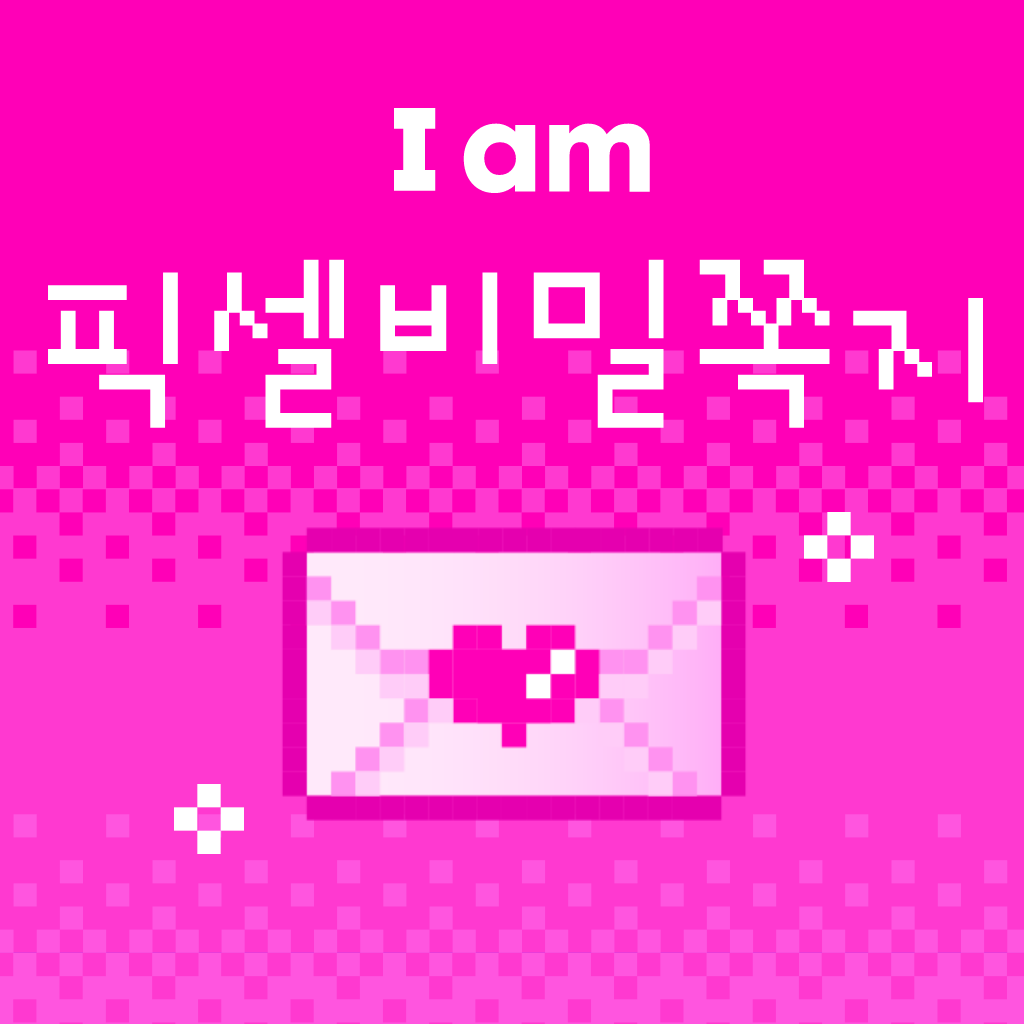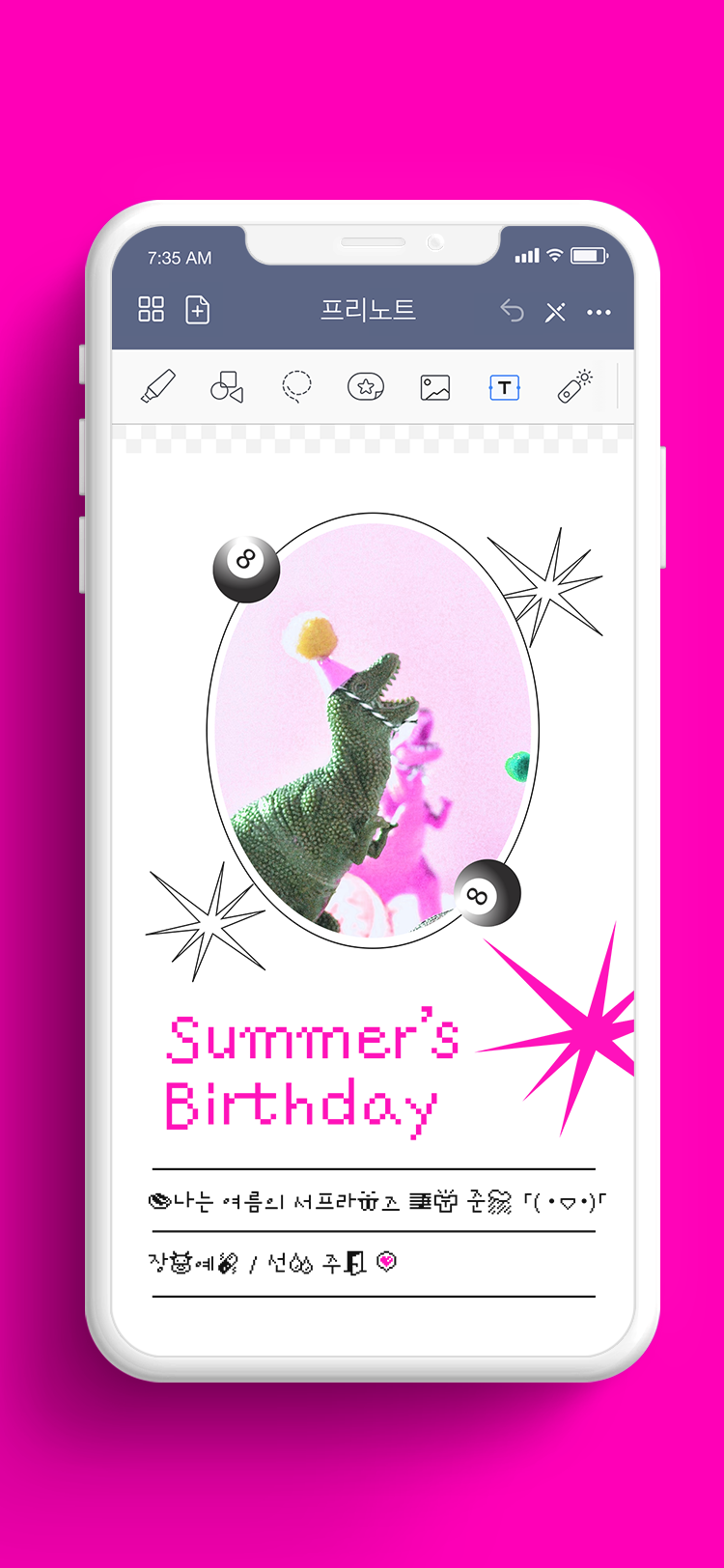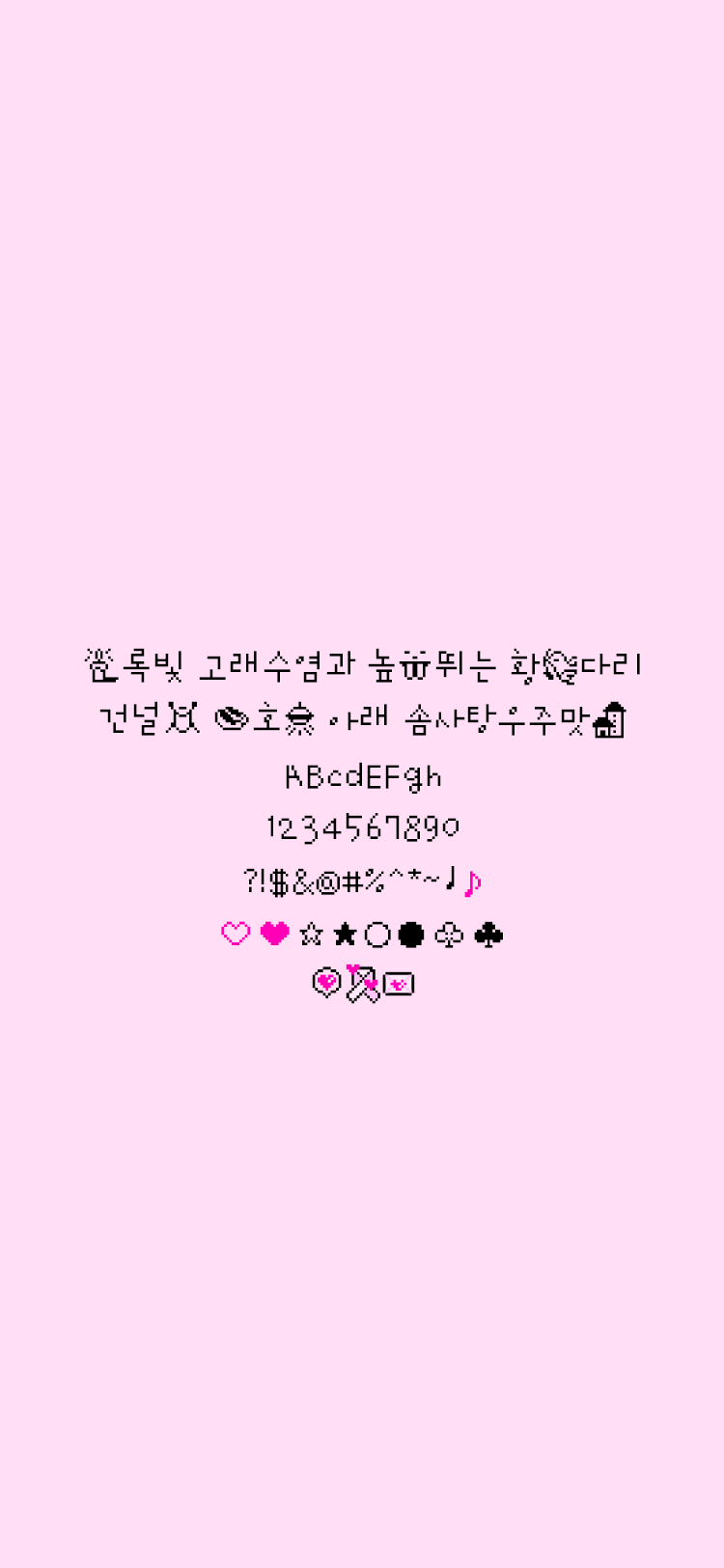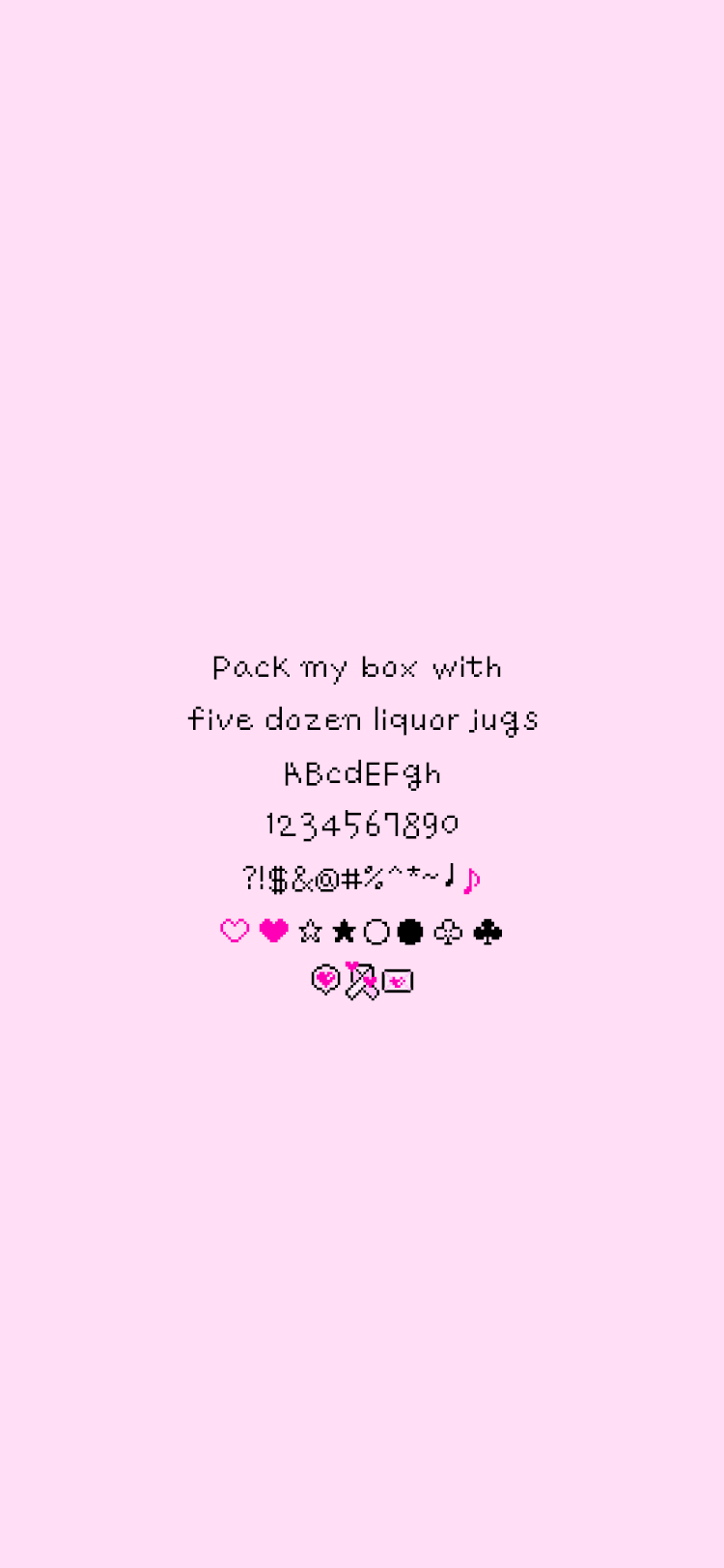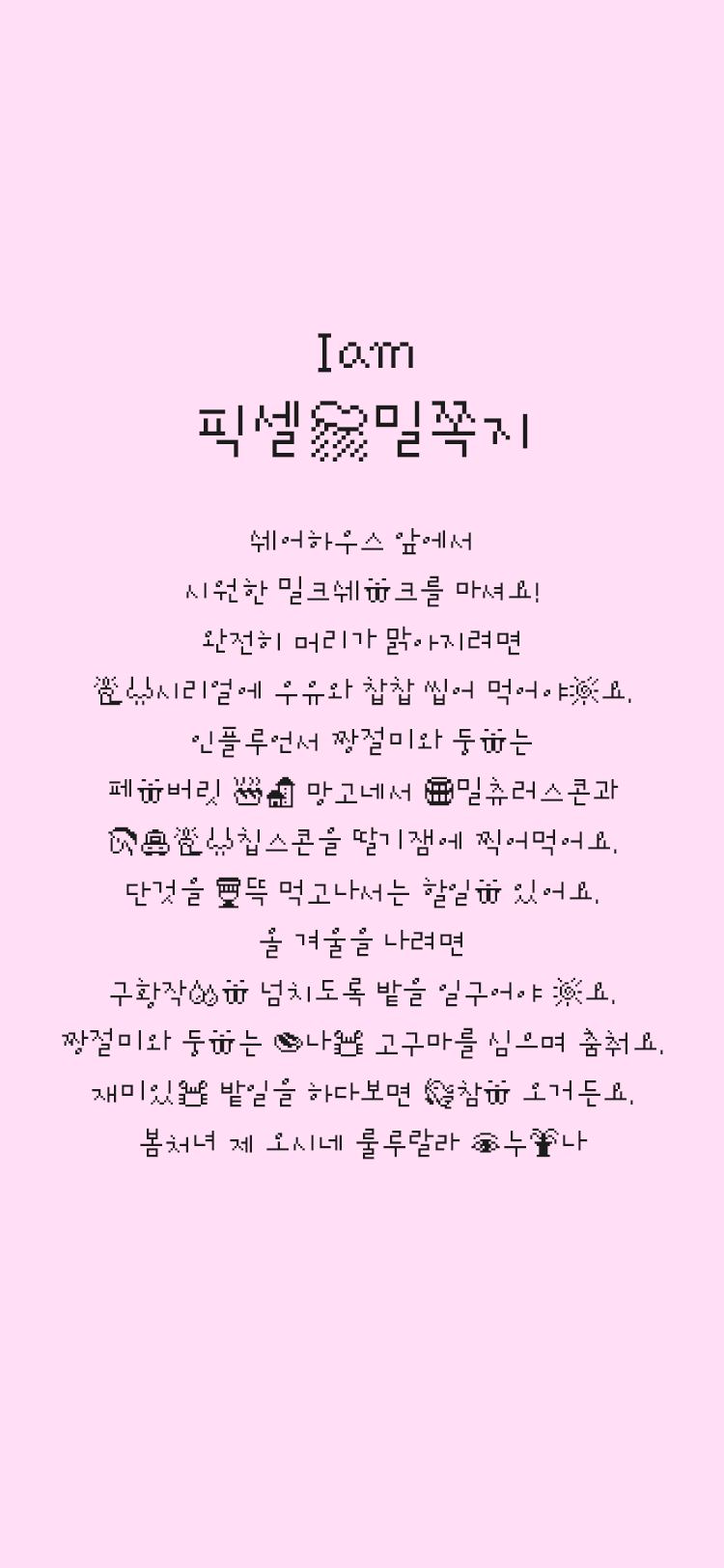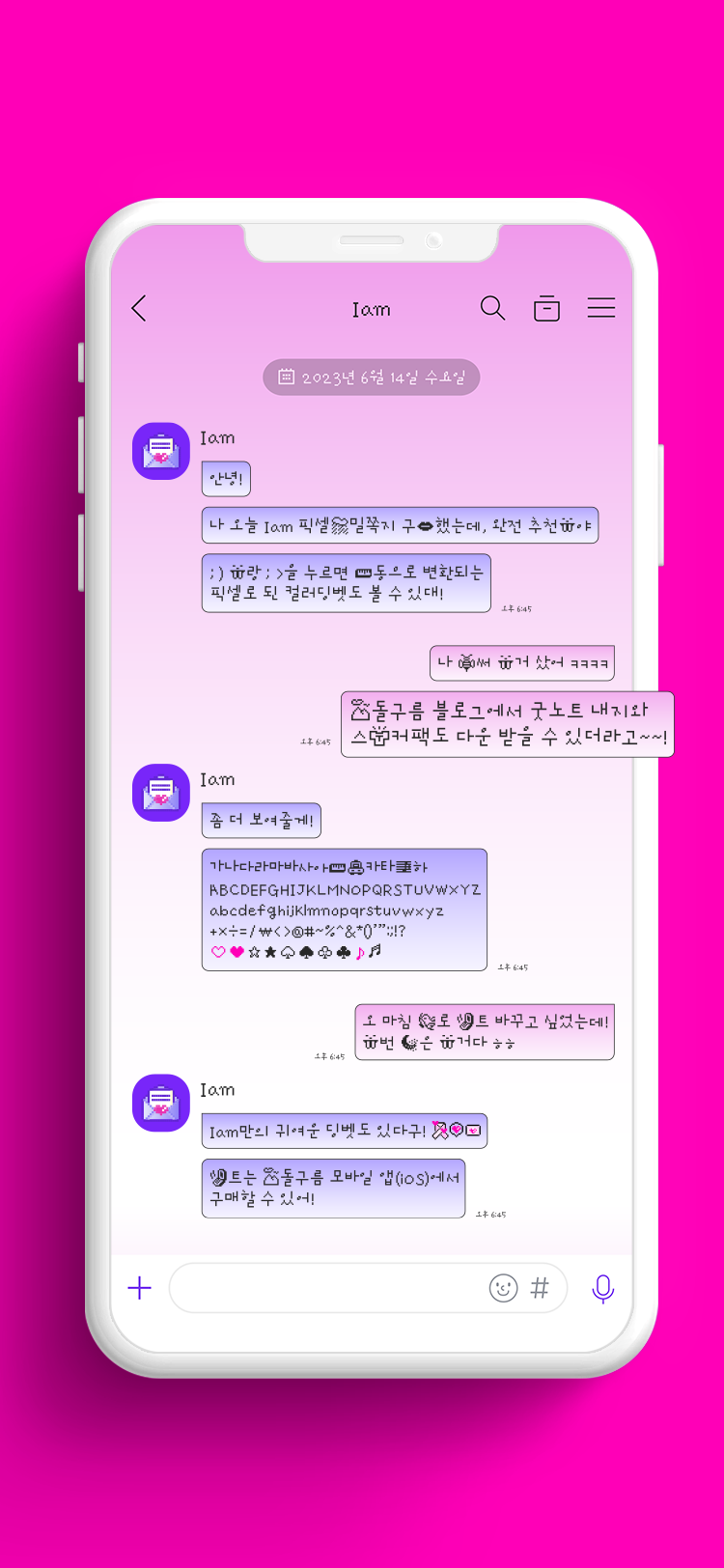
Iam 픽셀비밀쪽지 / Iam PixelBimiljjokji
♥ 내 친구 픽셀비밀쪽지를 소개합니다♥
그 때 그 시절 레전더리 산돌광수체가 쪽지라는 귀여운 애칭과 함께 픽셀 폰트로 돌아왔어요! Iam픽셀비밀쪽지는 Iam픽셀쪽지에서 103글자들이 딩벳으로 표현되어 소근소근 비밀쪽지를 주고 받는 듯한 재밌는 폰트예요!
키보드에서 ; ) 과 ; > 그리고 :!:을 눌러 귀여운 픽셀 딩벳들도 사용해보세요.
*103개의 글립은 다음과 같습니다.
[감개검게곰공굴귤금길꽃꿀난낫낮뇌눈달닭닻독돈돛등똥말목못묘무문물박발밤밥배백뱀벌별병복북불붓비빗빵뼈산삽새섬성소손솔솥술신실알약양연옷위이입잎자잔종쥐집차창책초총칼컵코콩퀸키킹탈탑톱통티파펜폰핀학해핵혀홈활]
*컬러 딩벳 기능을 지원하지 않는 브라우저 및 앱 환경에서는 흑백으로 표기됩니다. -